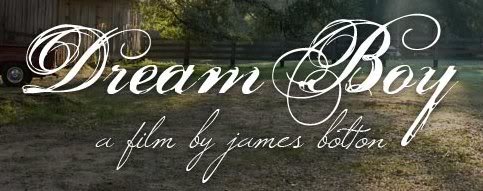
Welche Schrift(en)?
Welche Schrift(en) sind das auf dem Bild? Ist das die gleiche Schrift oder ist die untere eine andere? Sie ähnelt/n dem Chopin Script.